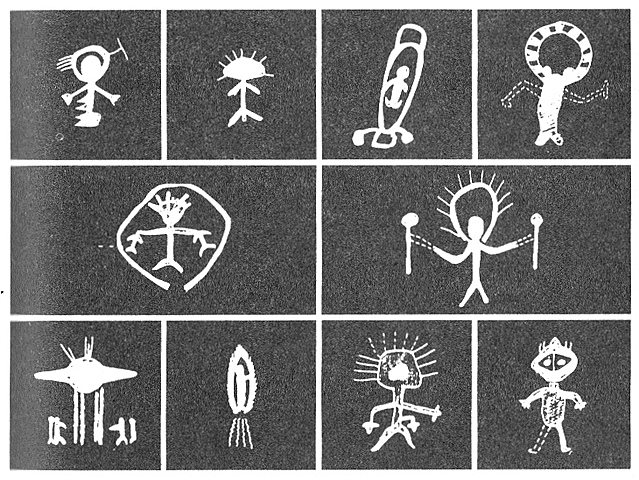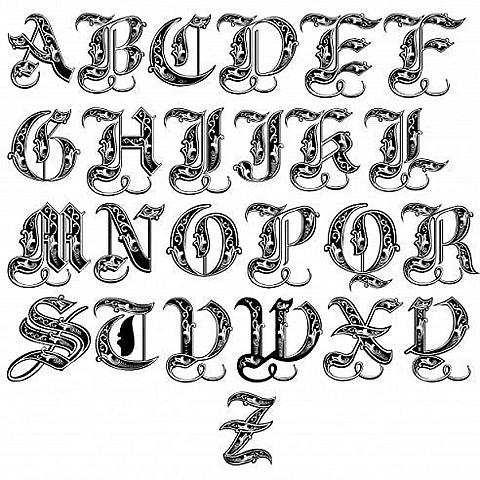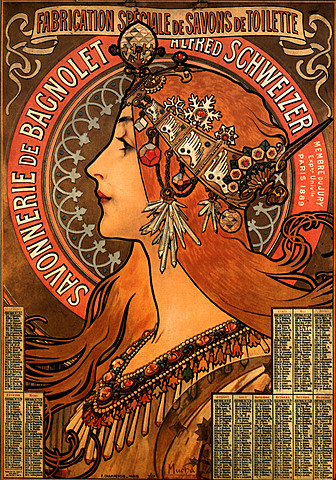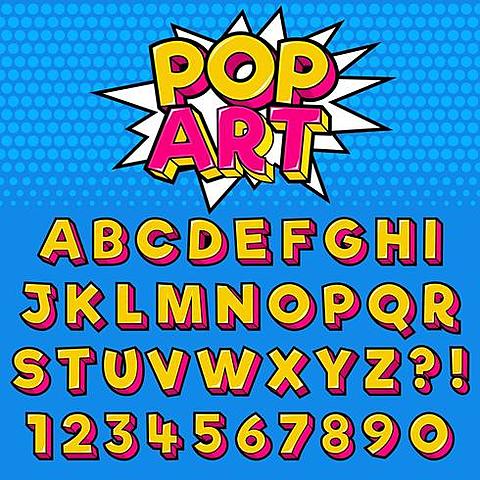
en la prehistoria el hombre registraba diversos acontecimientos a través de pictogramas. Las figuras que aparecen en las pinturas rupestres, por ejemplo, pueden considerarse como pictogramas. En el desarrollo de la escritura, los pictogramas fueron esenciales.
es un grafema, unidad mínima de un sistema de escritura que por sí sola representa una palabra, lexema o morfema. Esto contrasta con otros sistemas de representación no lingüísticos como los pictogramas o ideogramas, que plasman mensajes, o lingüísticos como los silabarios, donde cada símbolo representa en primer término un fonema (sonido) o combinación de ellos y no palabras enteras, lexemas o morfemas.
Mediante este sistema, el símbolo utilizado para denotar una determinada entidad pasa a convertirse en el símbolo que denota el sonido de la palabra que se emplea en la lengua hablada para hacer referencia a dicha entidad.
Los jeroglíficos fueron usados durante un periodo de más de 3.600 años para escribir la antigua lengua del pueblo egipcio. -
La escritura silábica es un conjunto de caracteres o símbolos escritos que representan (o aproximan) sílabas que forman las palabras. Un símbolo en un silabario normalmente representa un sonido consonántico seguido de un sonido vocálico.
La escritura la inventaron los sumerios en Mesopotamia hace unos 3,500 años A.C. aproximadamente. -
Los ideogramas son un modo de escritura donde un signo o un grupo de ellos son capaces de realizar la representación de una idea abstracta, y no sonidos. Los ideogramas son propios de algunas culturas como la japonesa, la del sur de Nigeria o la cultura china, y es uno de los modos más antiguos de expresión escrita, conservando sus rasgos esenciales por más de 3.700 años.
Un alfabeto es un conjunto de símbolos escritos que representan cada uno de ellos un sonido único.
El alfabeto recibe su nombre por las dos primeras letras griegas alfa y beta, que originalmente, en hebreo y en fenicio, significaban “toro” y “casa”; el alfabeto griego es una adaptación del alfabeto hebreo-fenicio. -
Desde la invención de la imprenta, creada por Johannes Gutenberg en 1440 con el sistema de
impresión de tipos móviles, el diseño de la tipografía se ha ido modificando y ha ido adquiriendo
características de los movimientos artísticos de cada época, además de incorporar los cambios
tecnológicos -
En 1900 tiene lugar el movimiento Art Nouveau con sus formas orgánicas imitando a la naturaleza
y el uso de colores pasteles. En esta época se diseña la tipografía Eckmann (creada por Otto
Eckmann) que es una extremada reinterpretación de la letra gótica. También en este período se
diseñan la Copperplate Gothic, de Frederic Goudy y la News Gothic de Morris Fuller Benton, creada
para la fundación American TypeFounders -
se diseñan las tipografías Imprint, Goudy Old Style y Centaur. En esta década aparecen dos
conceptos nuevos. Uno de ellos es la síntesis, técnica o procedimiento mediante el cual se hacen
desaparecer partes de la letra. El otro, es el recurso
de los ilustradores de incorporar a la tipografía como imagen, por lo que la tipografía deja de ser un elemento exclusivo para textos. -
El Art Decó en 1920 dejó su impronta en todas las artes (decorativas, gráficas, arquitectónicas,
joyería, escultura, cine y moda). Se dejan atrás las formas orgánicas y pasamos a las formas
geométricas. De hecho, con esta última aparece el
concepto de familia tipográfica y se diseñan muchas variables además de las clásicas "normal" o
"regular", "negrita" o "bold, "cursiva" o "itálica". -
Para 1960 se desarrollan los movimientos Pop Art y la Psicodelia, que combinan múltiples estilos
gráficos como el collage, texturas, fotografía, ilustraciones, etc. Pero también con la creación de
los ordenadores se comenzaron a demandar nuevas normalizaciones de códigos que pudieran ser
leídos por máquinas, como vemos en el ejemplo del título 1960 que contiene instrucciones alfabetonuméricas -
La década del 70 se caracteriza por el surgimiento y pedido de derechos de autor de los
diseñadores de tipos. Aparece el diseñador que se dedica exclusivamente al estudio y creación de
las letras. Se diseñan la American Typewriter de Joel Karden y Toni Stan; la Galliard de Matthew
Carter; la Chancery de Hermann Zapf -
Desde 1980 a nuestros días, han aparecido infinitas familias tipográficas. Si hablamos de diseño de
tipografía digital podemos decir que nació con Macintosh y que Steve Jobs fue su padre. Jobs, en
su obsesión por la estética, reunió a un grupo de diseñadores y artistas al mando del profesor en
caligrafía Robert Palladino, quien fuera su profesor en el Reed College de Portland, Oregón. Juntos
crean las primeras fuentes digitales como la Chicago, Geneva, Mónaco y Georgia (